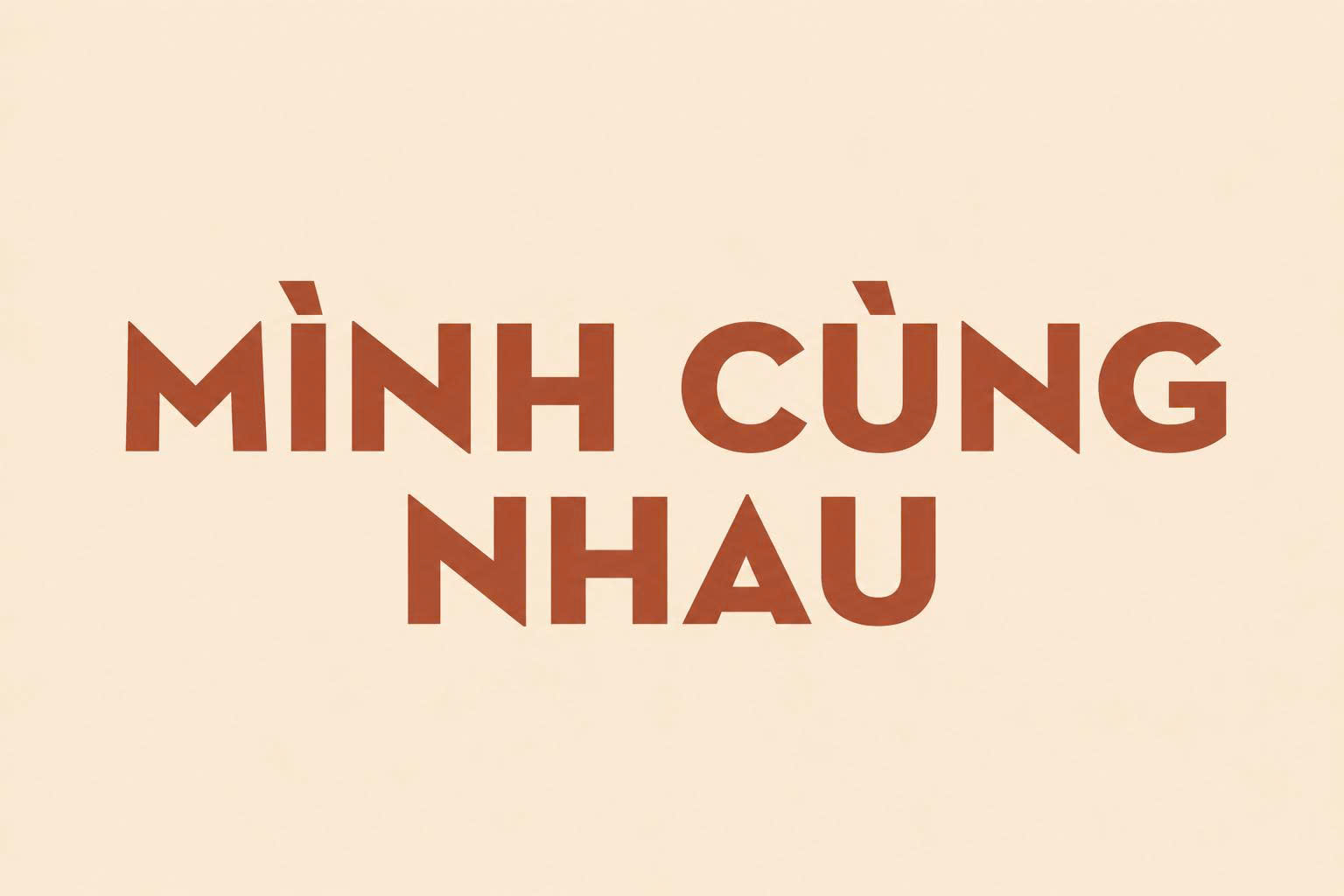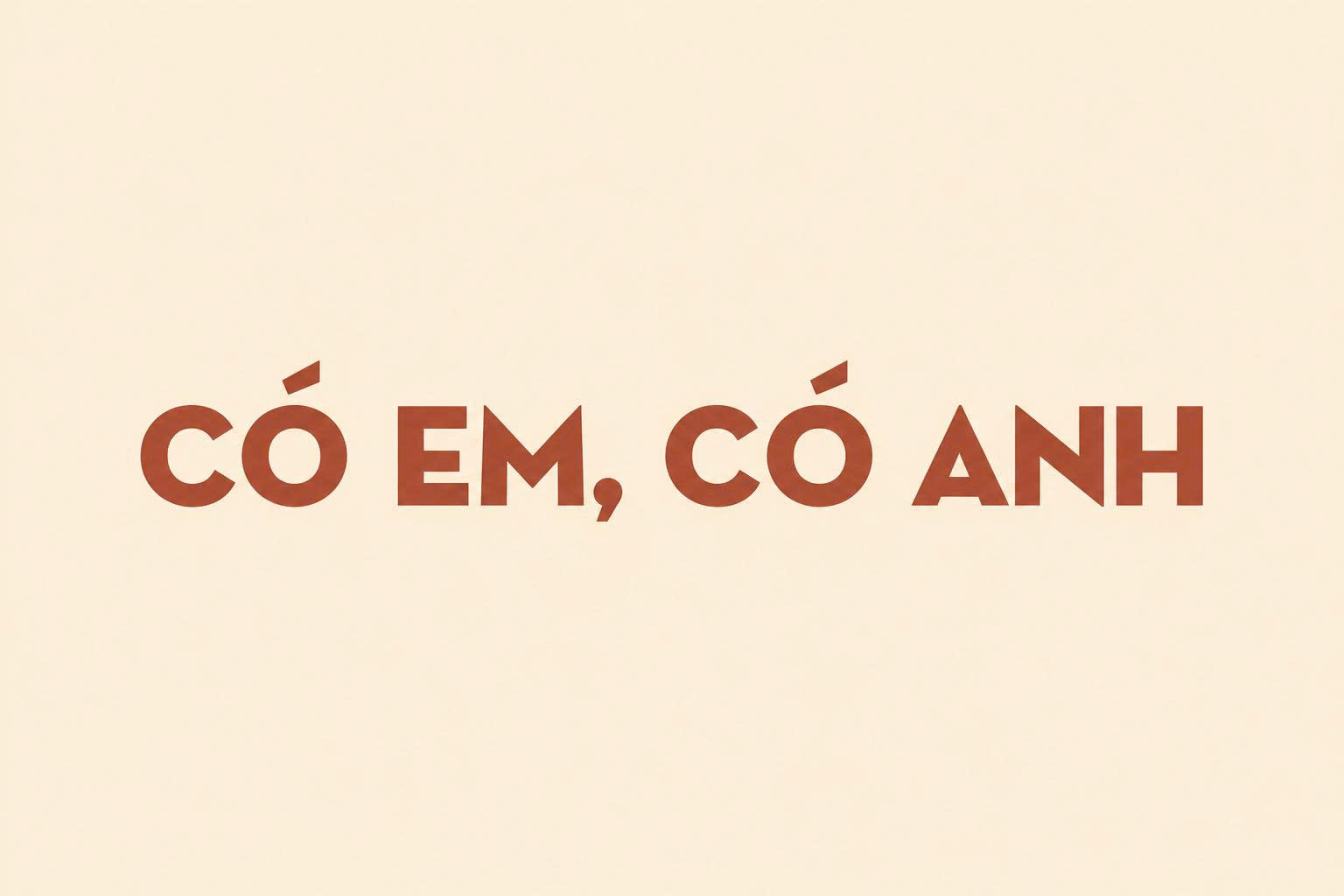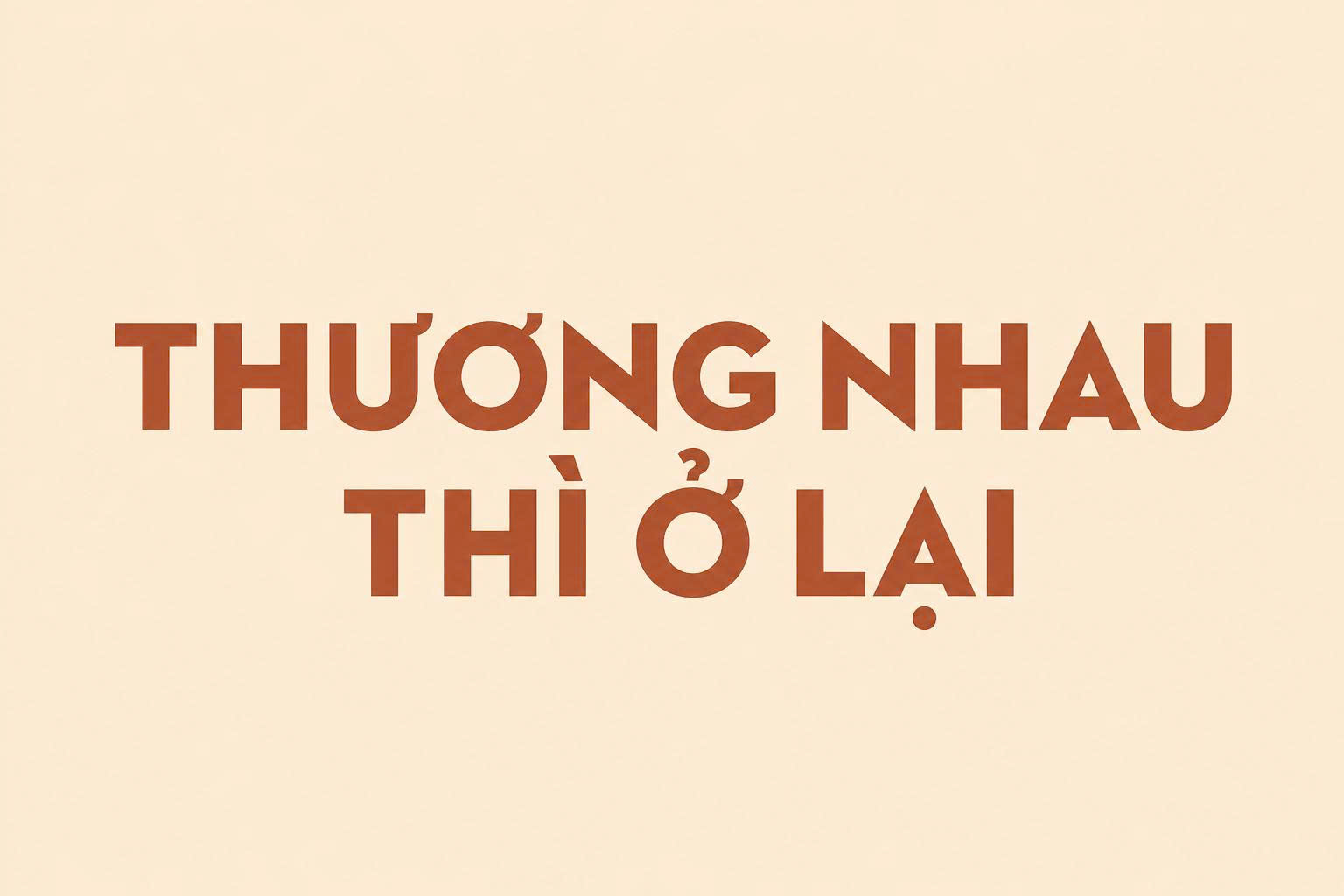
Font Việt hóa SVN Neutraface 2 – Tải font chữ hiện đại, chuyên nghiệp | Doozypack.vn
Font Việt hóa SVN Neutraface 2 là bộ phông chữ không chân (Sans-serif) mang phong cách hình học (Geometric) đỉnh cao, nổi bật với vẻ đẹp hiện đại, thanh lịch và vô cùng sang trọng. Lấy cảm hứng từ các nguyên tắc kiến trúc của Richard Neutra, bộ font này đã trở thành tiêu chuẩn vàng cho các thiết kế thương hiệu cao cấp, từ mỹ phẩm, thời trang đến kiến trúc và nội thất. Doozypack.vn chia sẻ link tải font svn-neutraface 2 việt hóa free chuẩn, giúp bạn sở hữu bộ phông chữ chỉn chu, hỗ trợ đầy đủ tiếng Việt để nâng tầm đẳng cấp cho mọi bản thiết kế bao bì.
Đặc điểm thiết kế tinh tế của font SVN Neutraface 2 Việt hóa
Neutraface 2 không chỉ là một phông chữ, nó là sự hiện diện của tư duy kiến trúc hiện đại trong đồ họa, mang lại cảm giác minh bạch và chuyên nghiệp tuyệt đối.
Font Việt hóa SVN Neutraface 2 phong cách hiện đại
Cấu trúc hình học hiện đại và sang trọng
Đặc trưng lớn nhất của font việt hóa svn neutraface 2 là sự cân bằng hoàn hảo giữa các đường thẳng dứt khoát và các đường cong toán học chính xác. Với x-height (chiều cao chữ cái thường) được tính toán kỹ lưỡng, font chữ này tạo ra một không gian văn bản thông thoáng, dễ đọc nhưng vẫn giữ được nét quý phái đặc trưng của các thương hiệu xa xỉ.
Hệ thống biến thể đa dạng phục vụ phân cấp thông tin
Bộ font này cung cấp nhiều độ dày khác nhau từ Thin, Light đến Bold, cùng các bản Display dành riêng cho tiêu đề lớn. Sự đa dạng này cho phép designer dễ dàng thiết lập quy tắc phân cấp thị giác (Typography Hierarchy) trên bao bì sản phẩm, giúp khách hàng nhanh chóng nhận diện được thông tin quan trọng nhất.
Font SVN Neutraface 2 Việt hóa với nhiều kiểu chữ
Tại sao designer nên download font SVN-Neutraface 2 Việt hóa cho bao bì?
Trong ngành sản xuất bao bì tại Doozypack.vn, SVN Neutraface 2 luôn nằm trong danh mục các font chữ “quyền lực” nhất nhờ tính ứng dụng vượt trội:
• Giải quyết lỗi hiển thị tiếng Việt: Việc sử dụng bản Việt hóa chuẩn giúp bạn gõ các tiêu đề như “Sản phẩm cao cấp” hay “Thương hiệu quốc tế” một cách mượt mà, bộ dấu thanh được thiết kế tinh tế hài hòa với thân chữ gốc.
• Tạo dấu ấn Luxury: Neutraface 2 mang lại diện mạo đắt tiền cho sản phẩm, đặc biệt hiệu quả khi ứng dụng trên các chất liệu giấy mỹ thuật cao cấp.
• Tiết kiệm thời gian thiết kế: Bạn không cần chỉnh sửa thủ công từng dấu lỗi, giúp quy trình từ bản vẽ đến xưởng in diễn ra nhanh chóng hơn.
Tư vấn từ chuyên gia: Để nội dung mô tả trên hộp giấy rõ nét nhất, bạn nên dùng biến thể Book hoặc Medium. Biến thể Thin rất đẹp nhưng chỉ nên dùng cho tiêu đề lớn hoặc in trên giấy Ivory phẳng mịn để tránh bị mất nét mực.
Ứng dụng thực tế của font Neutraface 2 trong sản xuất bao bì tại Doozypack.vn
Vẻ đẹp kiến trúc của Neutraface 2 mang lại hiệu quả thị giác đặc biệt trên các ấn phẩm tại Doozypack.vn:
• Hộp mỹ phẩm & Spa: Nét chữ thanh thoát của Neutraface 2 cực kỳ phù hợp cho vỏ hộp serum, nước hoa hoặc các bộ kit chăm sóc da cao cấp.
• Túi giấy doanh nghiệp: Tên công ty in bằng biến thể Bold tạo cảm giác vững chãi, uy tín và chuyên nghiệp khi khách hàng xách trên tay.
• Thiết kế Logo tối giản: Là lựa chọn hoàn hảo cho các thương hiệu theo đuổi phong cách Minimalism, nhấn mạnh vào sự tinh tế và đẳng cấp.
Ứng dụng font Việt hóa SVN Neutraface 2 trên bao bì
• Điều chỉnh khoảng cách dòng (Leading): Với cấu trúc chữ hiện đại, bạn nên đặt khoảng cách dòng rộng hơn mặc định (khoảng 1.4 – 1.5 lần size chữ) để khối văn bản trông thông thoáng và dễ đọc hơn trên nền giấy thực tế.
• Kích thước chữ tối thiểu: Trên chất liệu giấy Ivory nhẵn mịn, font rõ nét ở 6pt. Tuy nhiên, trên giấy Kraft nhám, bạn nên để tối thiểu là 7.5pt để các dấu tiếng Việt không bị nhòe mực.
5. Làm sao để in font Neutraface 2 trên túi giấy Kraft đẹp nhất?
Doozypack.vn khuyên bạn nên chọn màu in đậm và biến thể Medium trở lên. Sự kết hợp giữa nét chữ hình học hiện đại và chất liệu giấy Kraft mộc mạc sẽ tạo nên phong cách “Modern Eco” cực kỳ ấn tượng.